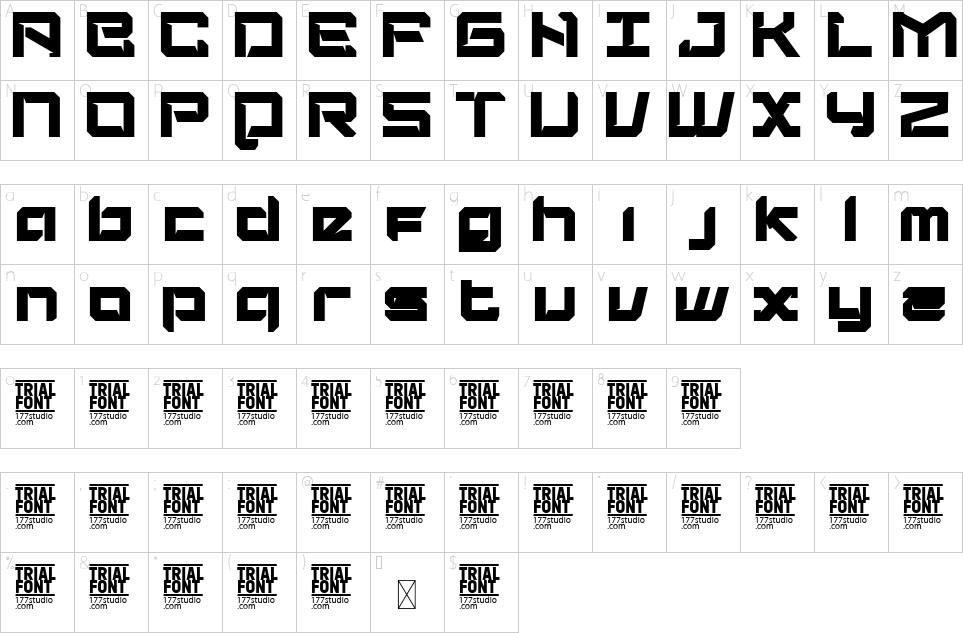
A Deeply Rooted é uma elegante fonte que traz consigo um toque profundo e sofisticado para qualquer projeto, seja ele em sua versão Windows ou Mac. Ela foi projetada pela inestimável equipe de 177studio.com, que tem demonstrado um talento excepcional em criar design gráfico único e envolvente. Com uma linhas arquitetonicamente perfeitas e uma paleta vibrante de cores, a Deeply Rooted é ideal para qualquer aplicação de texto, desde editoriais até design de gráficos. A fonte já foi descarregada 478 vezes, um número que testemunha o valor e qualidade deste recurso gráfico livre. Com seu traço sóbrio e detalhado, a Deeply Rooted oferece uma textura única que cria profundidade e interesse visual, tornando-a uma escolha atraente para designers de todos os níveis. Seja você um profissional experiente ou iniciante no campo da gráfica, a Deeply Rooted é uma fonte perfeita para sua coleção de recursos digitais gratuitos.